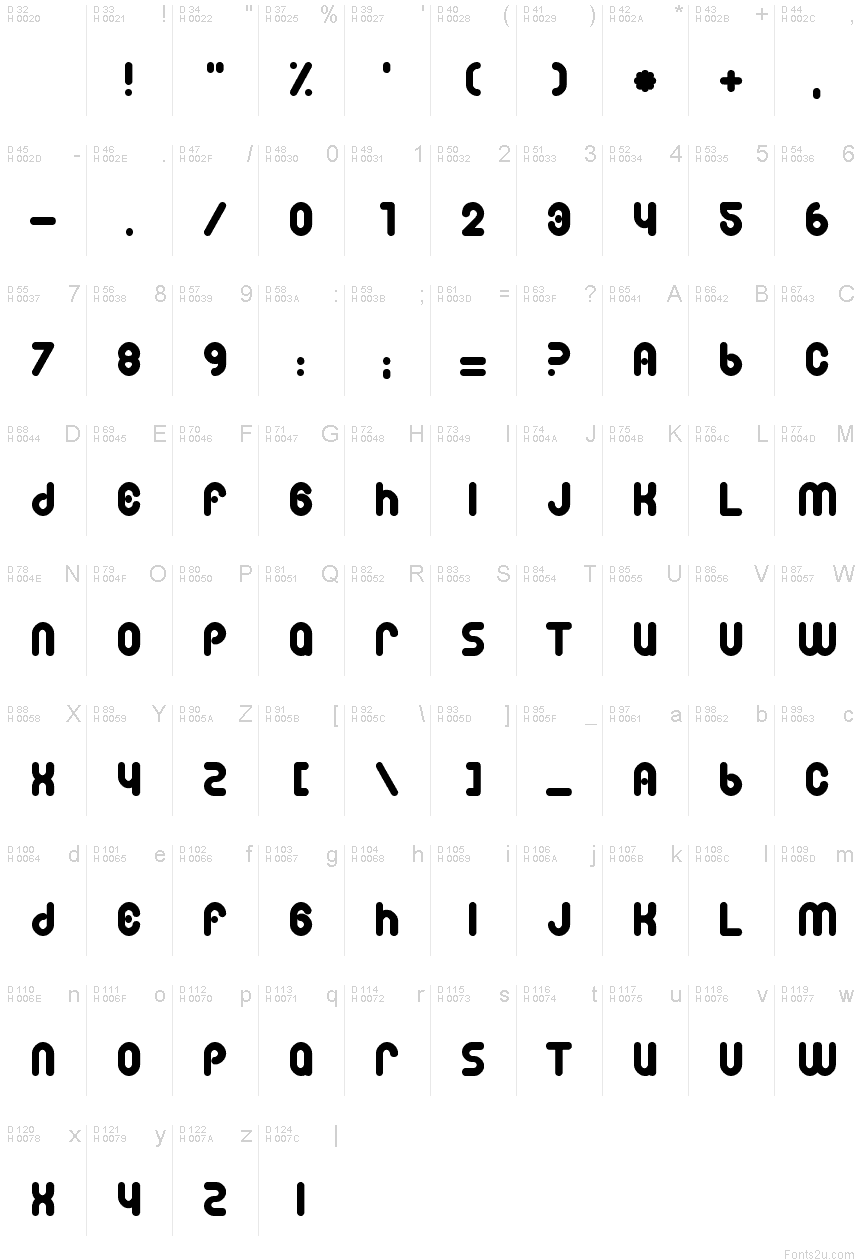
Tesh هو خط عرض عصري ومجاني، يتميز بحروف ممتلئة ودائرية وإيقاع ناعم ومضغوط. يبدو التصميم مرحًا ولكنه متزن؛ فالخطوط العريضة والمنحنيات الملساء تضفي عليه لمسة من طابع الـ retro-tech الذي يجعله مميزًا دون أن يخرج عن إطار الاحترافية.
يعمل الخط بشكل رائع في تصميم هوية التطبيقات، وأغلفة الأعمال الموسيقية، وعناوين الملصقات، وتصاميم الـ streetwear، والتغليف الجذاب حيث يحتاج النص القصير إلى مظهر ممتلئ وناعم. وباعتباره خطًا مجانيًا، فإن Tesh مناسب أيضًا لبطاقات العناوين، وترويسات التواصل الاجتماعي، واسكتشات الشعارات، خاصةً عندما تبحث عن مظهر قوي وبارز يبدو وديًا وليس صارمًا.
Tesh